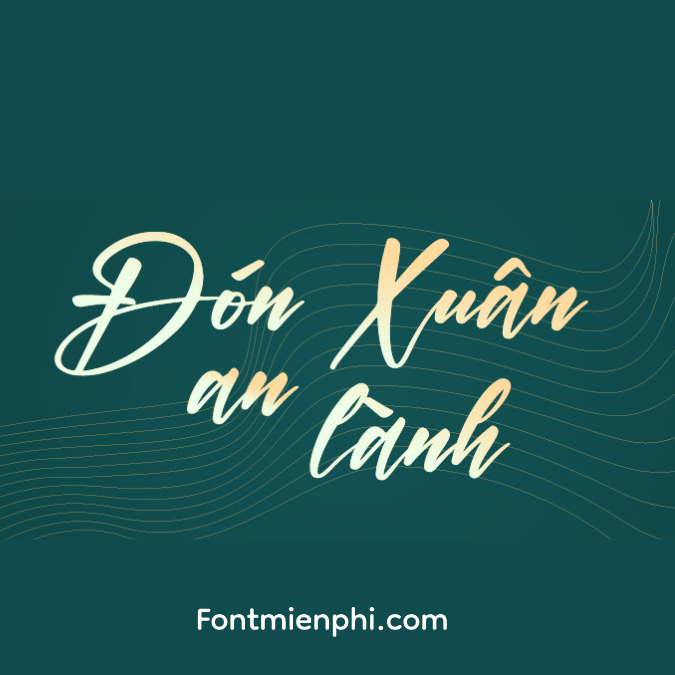
FONT VIỆT HÓA 1FTV VIP DITA
“Tinh hoa kiểu chữ cổ điển – Đẳng cấp vượt thời gian”
ĐẶC ĐIỂM NỔI BẬT
✒️ Phong cách Serif cao cấp: Lấy cảm hứng từ typography thế kỷ 18, kết hợp nét thanh đậm hài hòa
️ Độ tương phản hoàn hảo: Tỉ lệ nét mảnh/dày được tính toán chuẩn xác cho thiết kế in ấn
Tối ưu đa ngôn ngữ: Hỗ trợ full bộ dấu tiếng Việt + bộ ký tự Latinh mở rộng
ỨNG DỤNG CAO CẤP
• Nhận diện thương hiệu sang trọng (đồng hồ, rượu vang, trang sức)
• Ấn phẩm cao cấp (tạp chí, catalogue)
• Bao bì sản phẩm hạng sang
• Thiết kế sách bìa cứng cao cấp
BỘ VIP ĐẶC BIỆT
4 phiên bản độc quyền:
- Regular (nét chuẩn)
- Italic (nét nghiêng thanh lịch)
- Display (dành cho headline)
- Rough (hiệu ứng vẽ tay)
“Dita – Kiệt tác typography cho thương hiệu đẳng cấp”